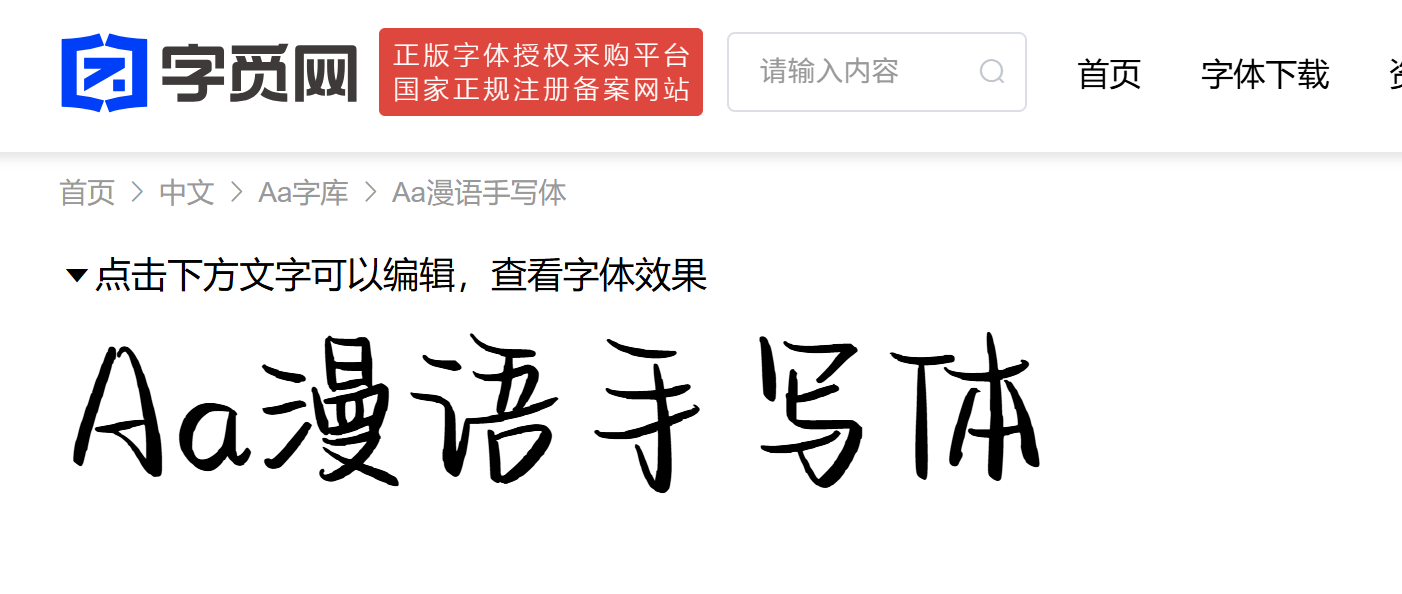
Aa漫语手写体是一款融合中国传统文化与漫画元素的手写风格字体,具有简洁美观、实用性强且富有想象力的特点。以下是关于该字体的关键信息:
一、核心特点
1、设计理念
整合书法、拼音与漫画元素,形成开放中宫和稳定笔画的独特风格
适合屏显及标题使用,兼具古韵与现代感
2、技术参数
支持简繁体,字符数超10,000,字重中等
三、应用场景
1、数字创作
2、设计领域